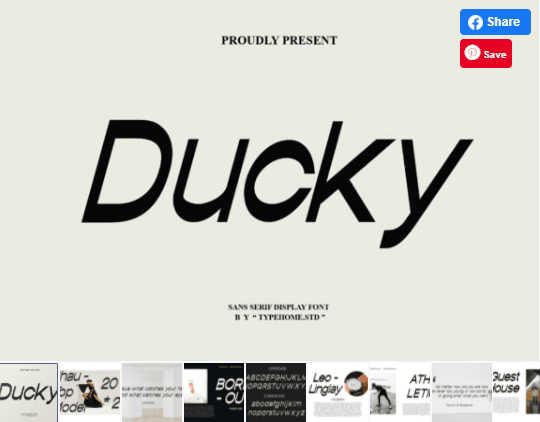
Ducky Font
Ducky - это минималистичный и изящный шрифт без засечек. Его можно легко сопоставить с невероятно большим набором проектов, поэтому добавьте его к своим творческим идеям и обратите внимание, как они выделяются среди них!